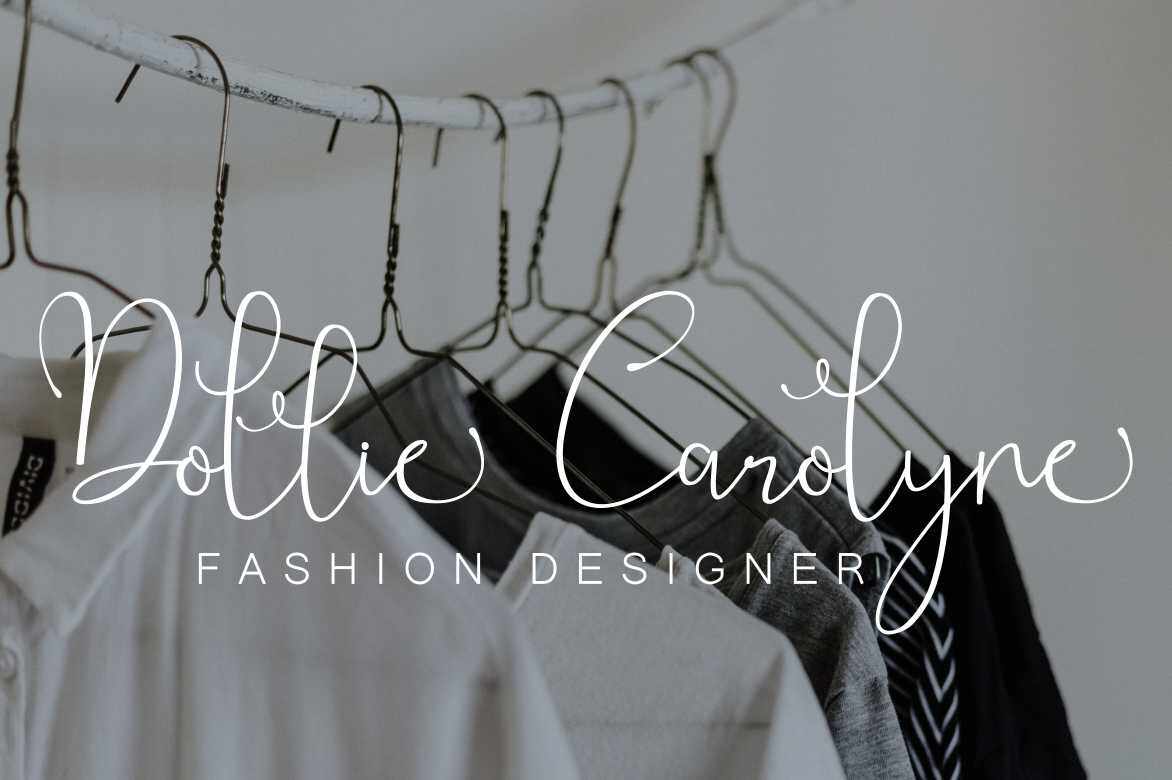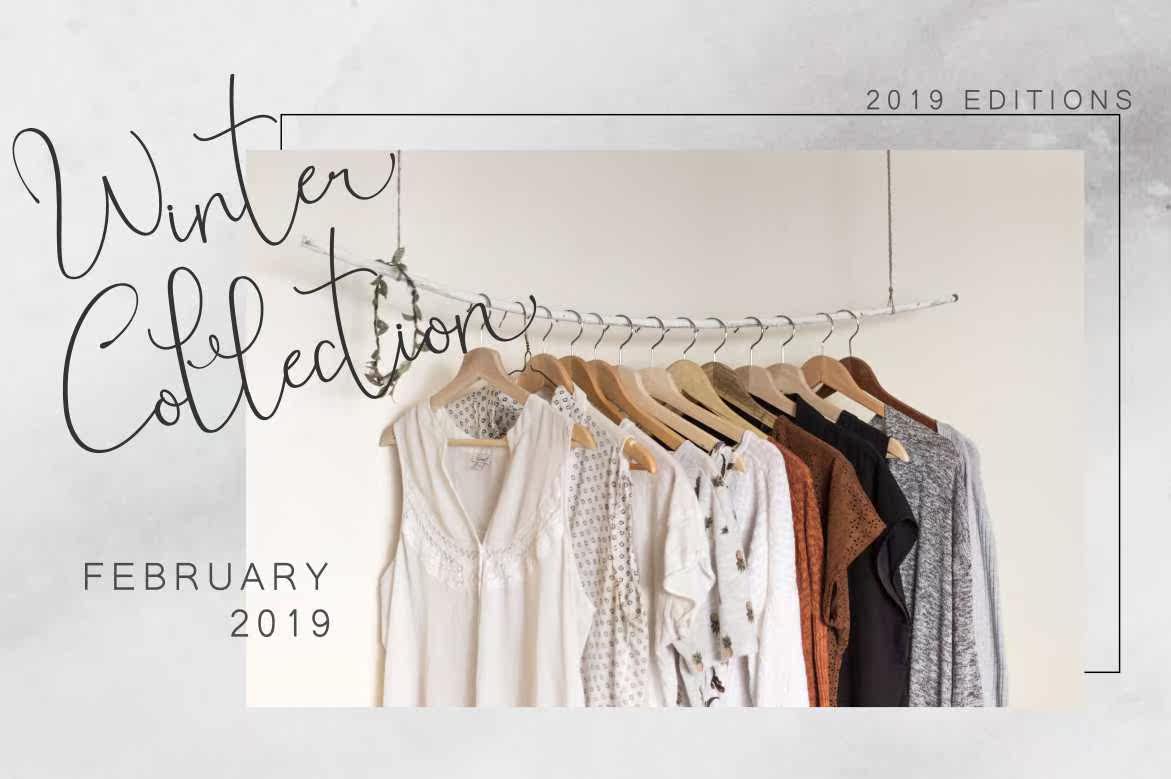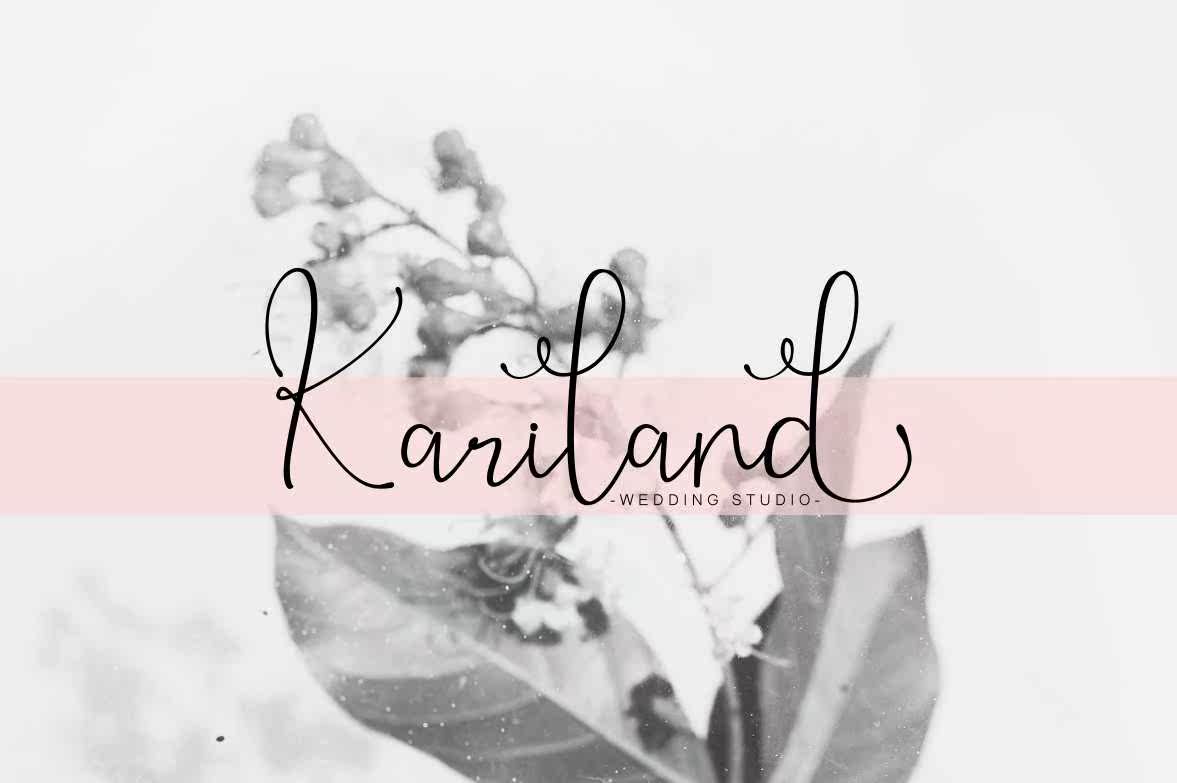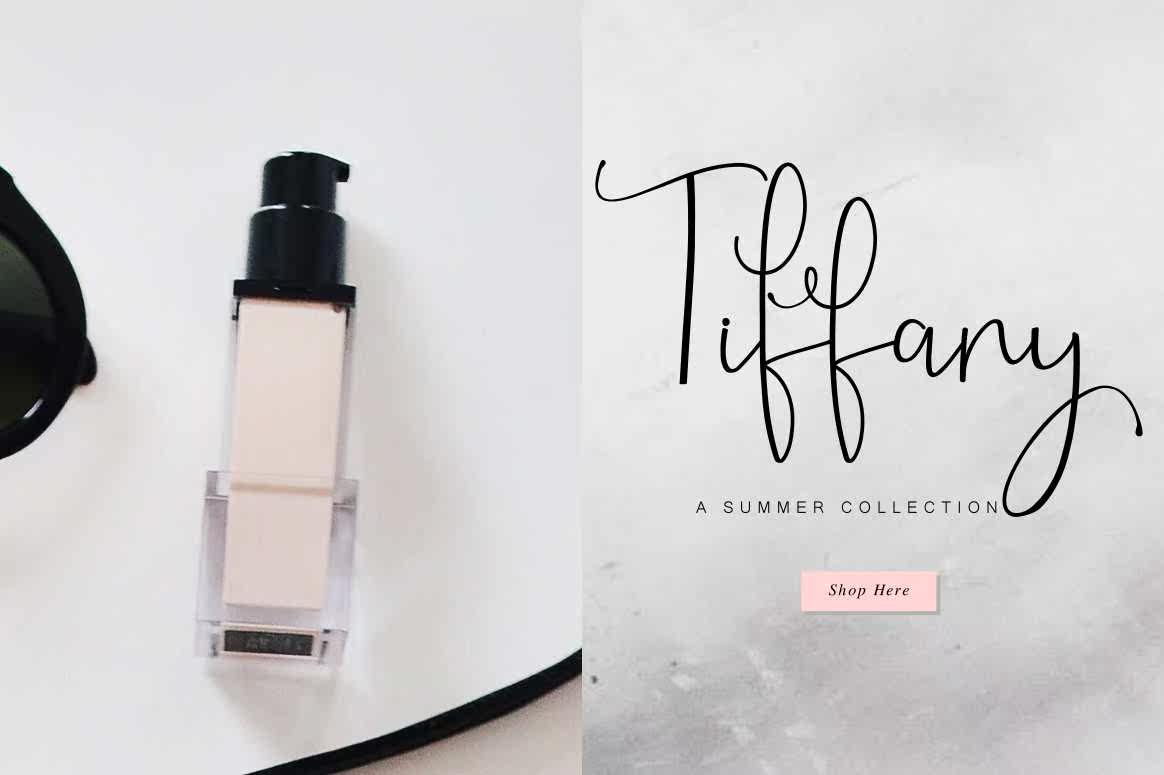
Millowscript Fresh and Modern Script.手工贴花印刷风格,字体为Kontenporer,具有基本的色彩、古典风格和独特的触感。可用于各种用途。对贺卡、杂志、名片、报价、海报、签名、徽标、婚礼宣传、信头、珍品、头条新闻、报纸、t恤、标牌、标签、光盘、,以及所有类型的办公设备等。Millowscript Fresh and Modern Script。手工贴花印刷风格,字体为Kontenpore,具有基本的色彩、古典风格和独特的触感。可用于各种用途。对贺卡、杂志、名片、报价、海报、签名、徽标、婚礼宣传、信头、珍品、头条新闻、报纸、t恤衫非常感兴趣,标牌、标签、光盘和所有类型的办公设备等。